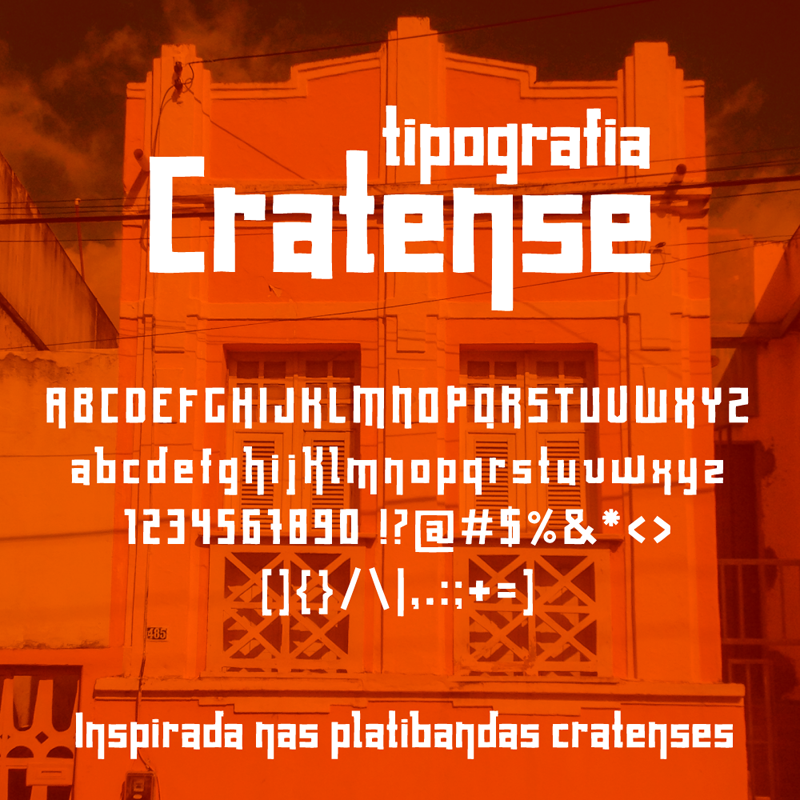
Font name: | Cratense |
Author: | Lucélia Barbosa |
Note by Lucélia Barbosa | |
Com intuito de preservar e promover a memória histórica do Crato, a tipografia "Cratense" foi inspirada na arquitetura nordestina e desenvolvida a partir do registro fotográfico das platibandas do Centro da cidade. As platibandas ainda são muito frequentes na cidade e deixaram como forma de expressão artística dos mestres pedreiros marcas únicas e se tornaram identidade das pequenas cidades. Por ser display é um tipo ideal para títulos e textos curtos. |